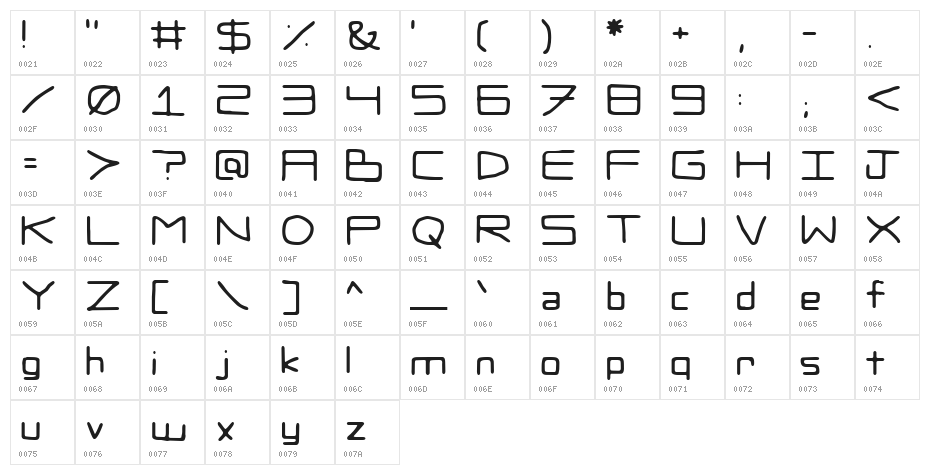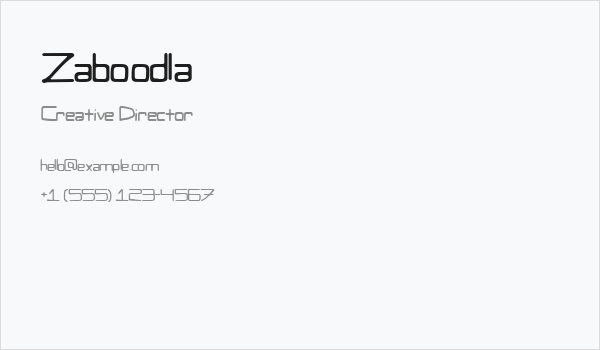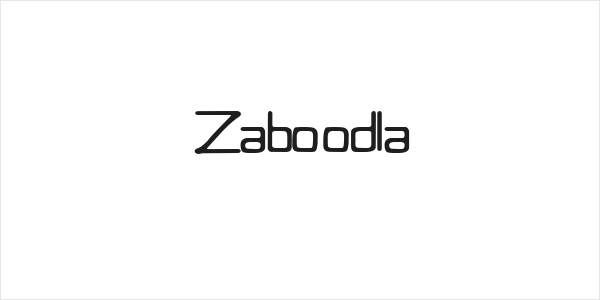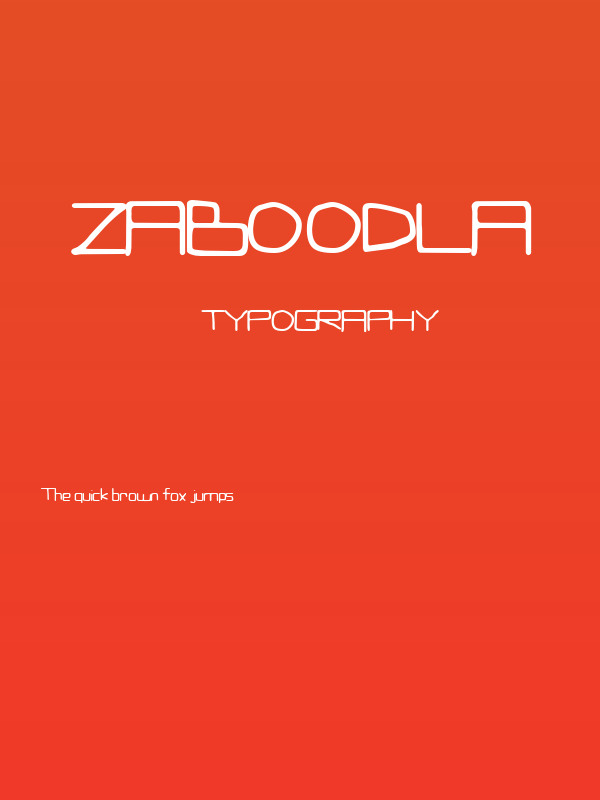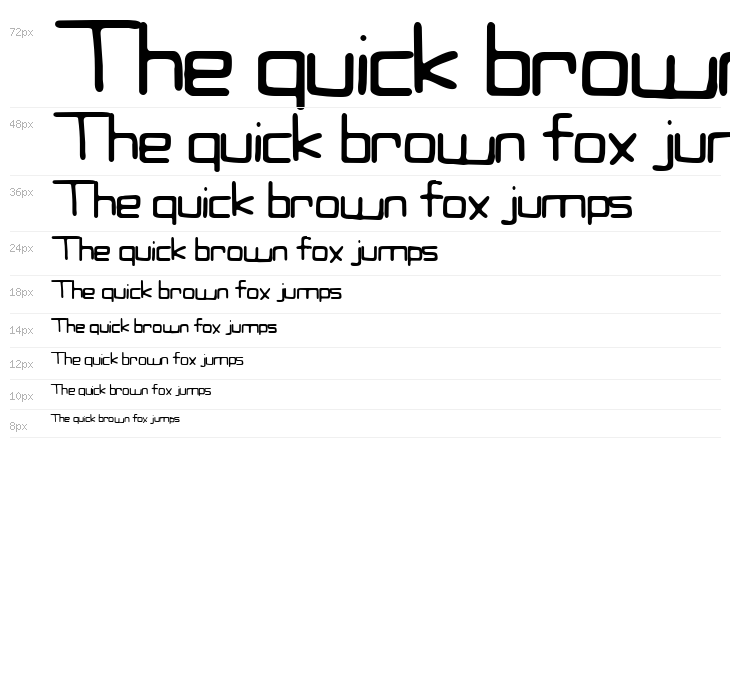
Zaboodla Font
| Caso de uso | Headlines, Logos, Digital Interfaces |
| Proyectos propuestos | Perfect for tech-related branding, modern advertising, digital interfaces, and futuristic-themed projects. |